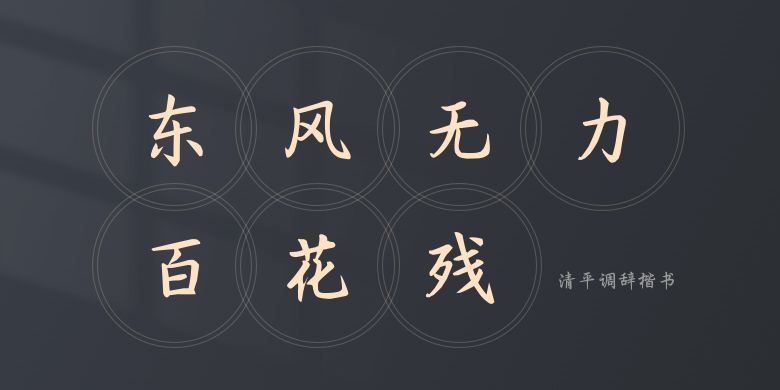
清平调辞楷书
清平调辞楷书,这款字体结构工整、笔画清晰,兼顾美观与易读性,适用于标题、正文、海报、包装、LOGO 等多种场景。字形优雅稳定,风格百搭耐看,适配日常排版与创意设计,让文字呈现更舒适、更具质感。清平调辞楷书一笔一画,皆是细节,以均衡的比例、流畅的线条打造舒适视觉体验,字形端正大气,风格简约现代。无论是商业设计、品牌宣传还是日常排版,都能轻松驾驭,让文字更有格调与力量。清平调辞楷书字体下载。